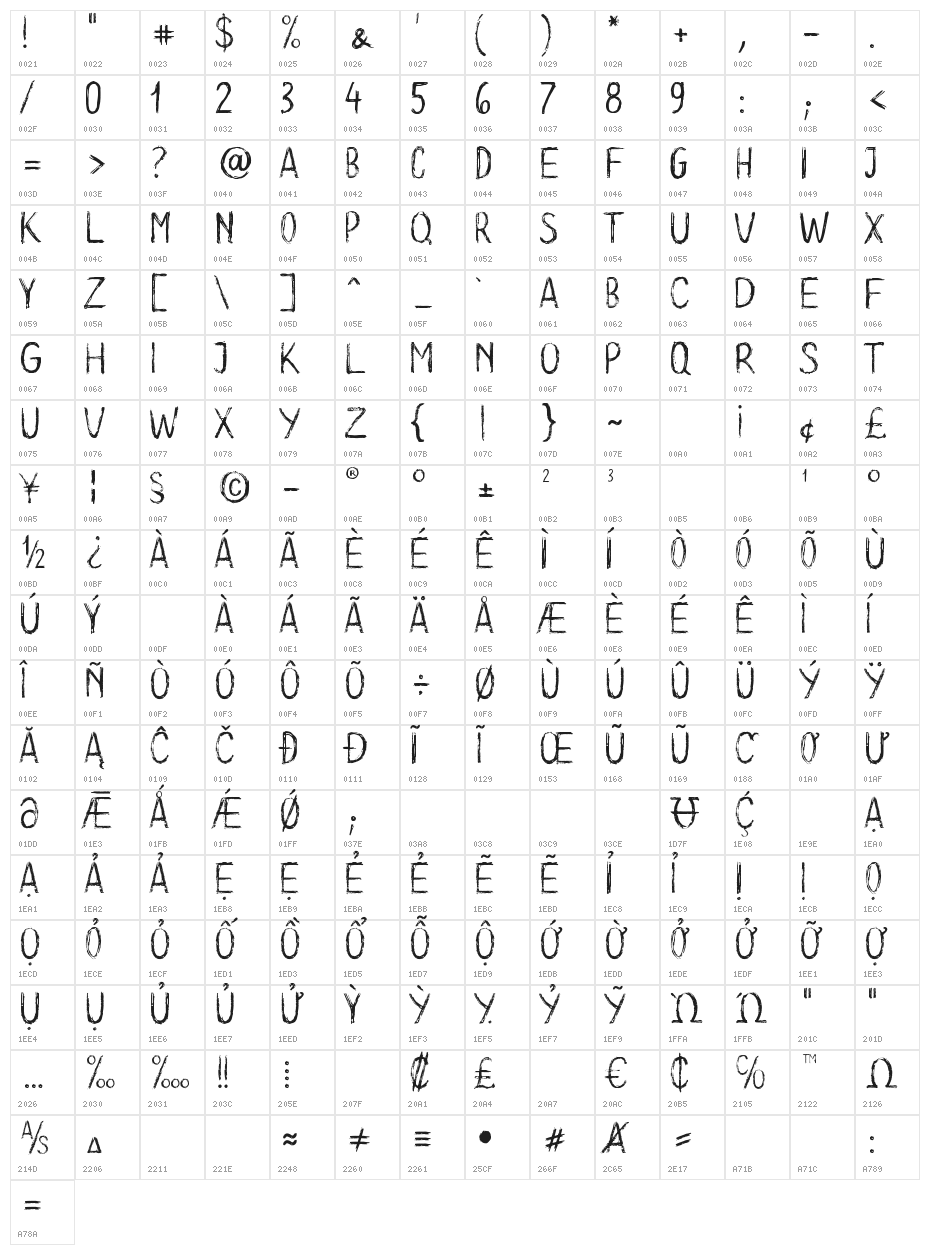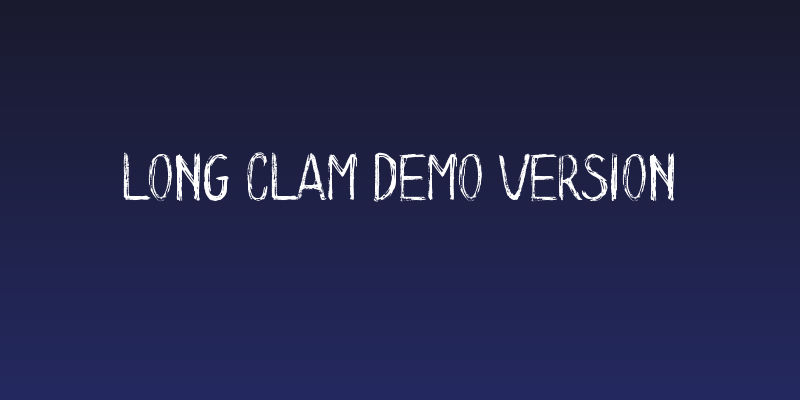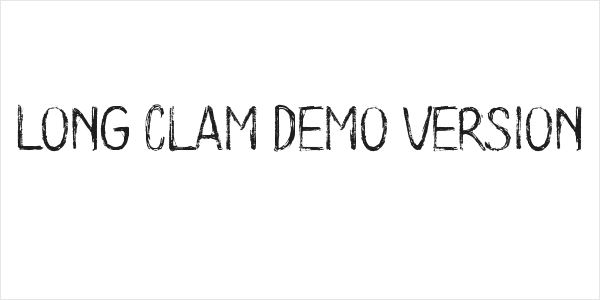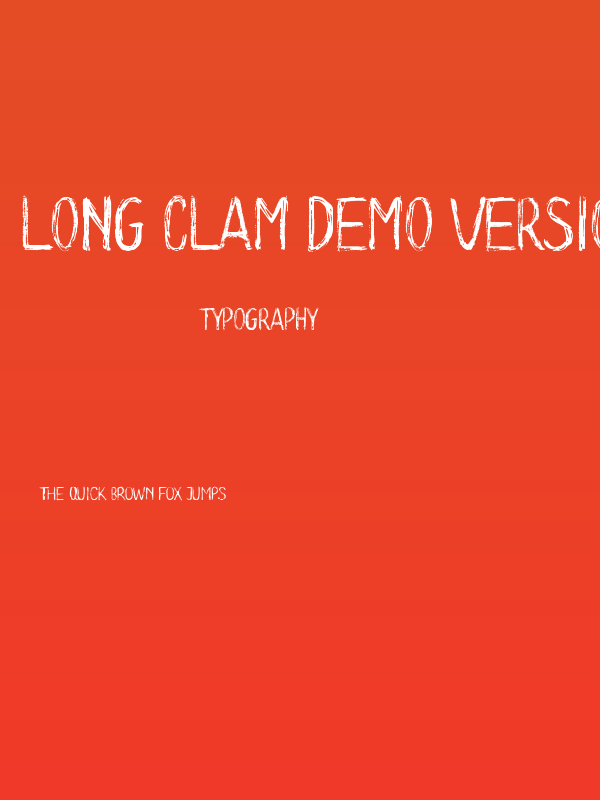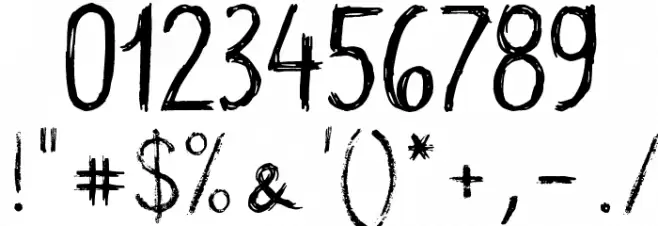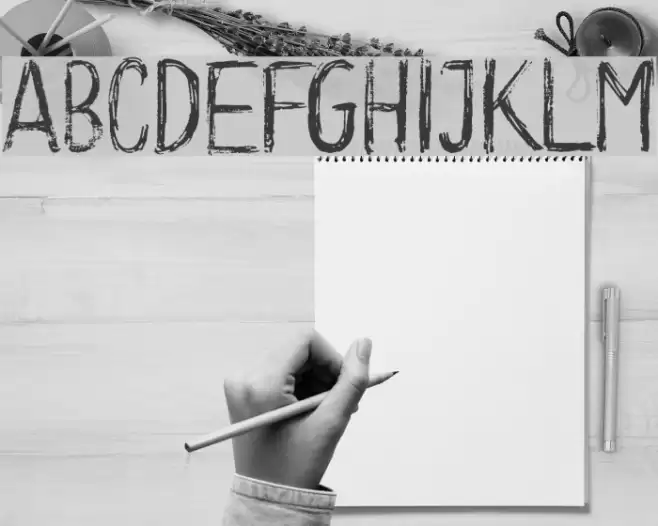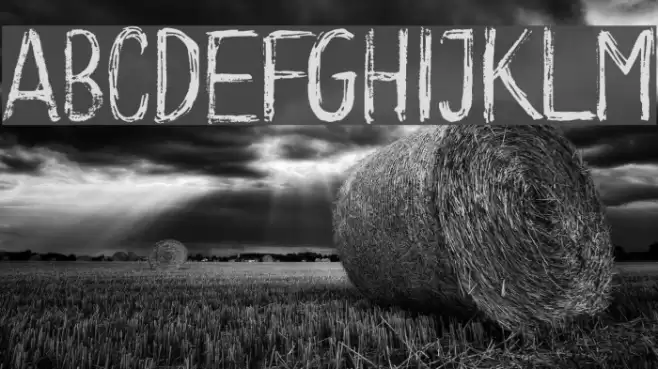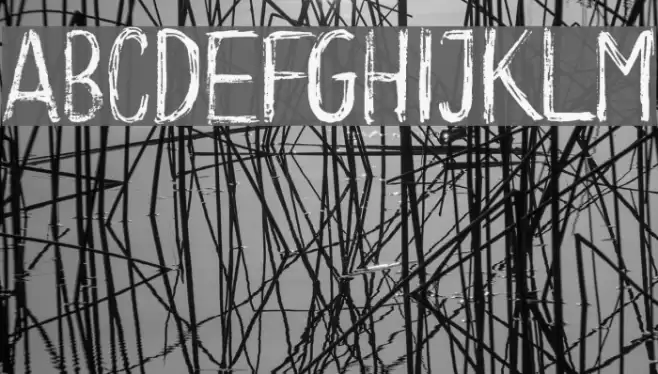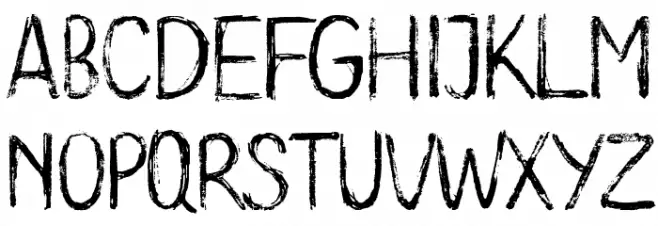
Long Clam Demo Version Font
| Рекомендуемые проекты | Perfect for posters, album covers, branding for edgy or artistic products, and any design needing a bold, creative flair. |